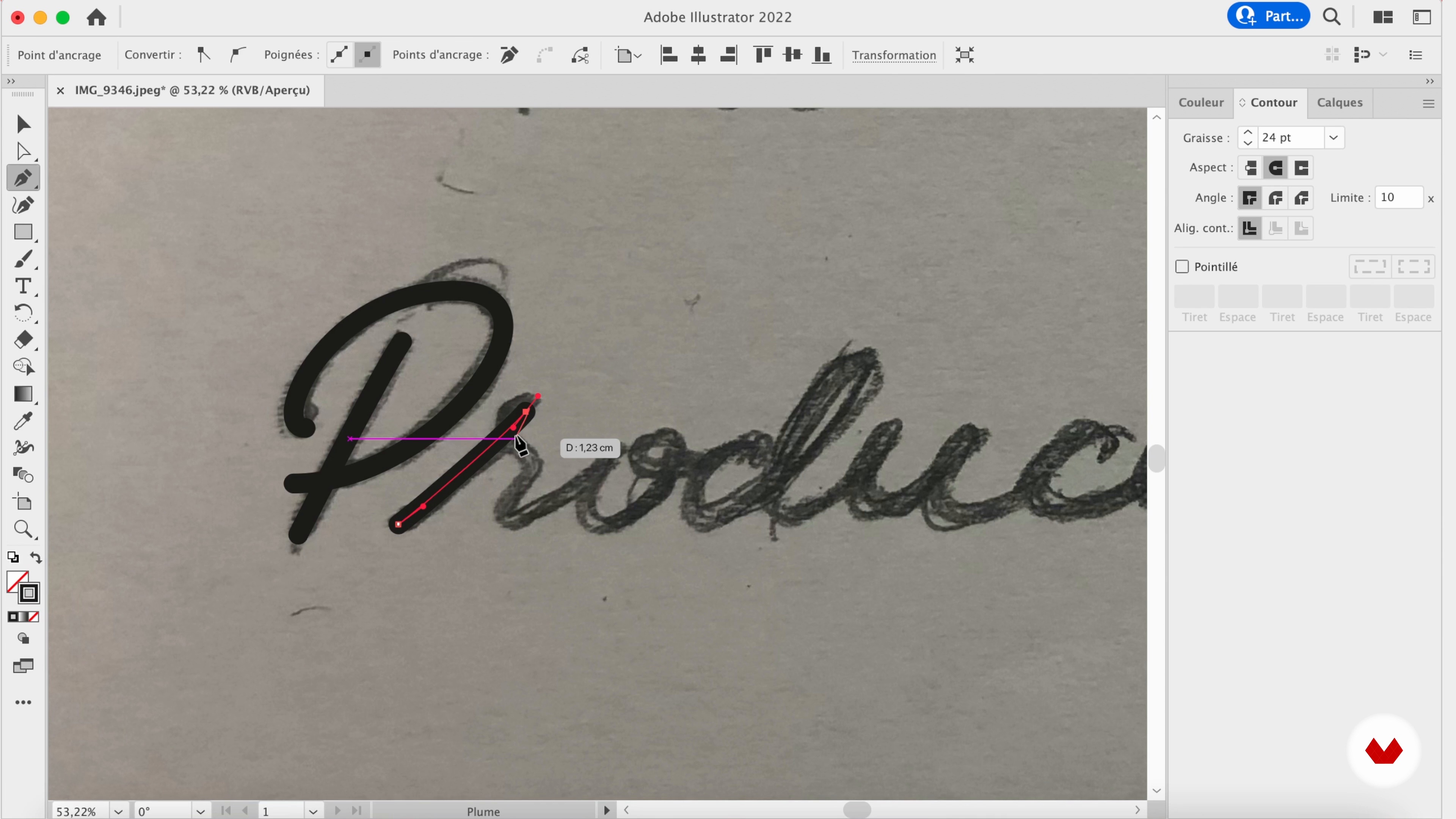
Die Typografie
Über die Videolektion: Die Typografie
“Jetzt werde ich Ihnen zeigen, wie ich Typografie erstelle, zuerst auf Papier und dann mit Illustrator. In diesem Fall versuche ich, in der Typografie das Bild eines Kabels zu reproduzieren, das mit Pats Helm verbunden wäre.”
In dieser Videolektion behandelt Charlotte Delarue das Thema: Die Typografie, das Teil dieses Domestika-Onlinekurses ist: Bleistiftillustration für Plattencover. Gestalte ein beeindruckendes Albumcover mit Bleistift und realistischen Illustrationstechniken, von der Skizze und Fotomontage bis hin zur Typografie.
Partielle Transkription des Videos
“Die Typografie In dieser Lektion Ich zeige Ihnen, wie Sie die Kabeltypografie festlegen. Wann immer ich eine Typografie entwerfe, Ich muss immer die Zeitung durchgehen die Buchstaben mehrmals zu zeichnen, bis Sie mit dem Ergebnis zufrieden sind bevor Sie zur Illustrator-Software wechseln um die Typografie sauber zu machen. Die Idee hinter dieser Typografie ist, dass sie von einem Kabel inspiriert ist. Ich werde versuchen, dies so weit wie möglich zu reproduzieren. Ich werde Buchstaben zeichnen die selbst in das Kabel integriert werden, die mit Pats Helm verbunden ist. Bei diesem ganzen Teil...”